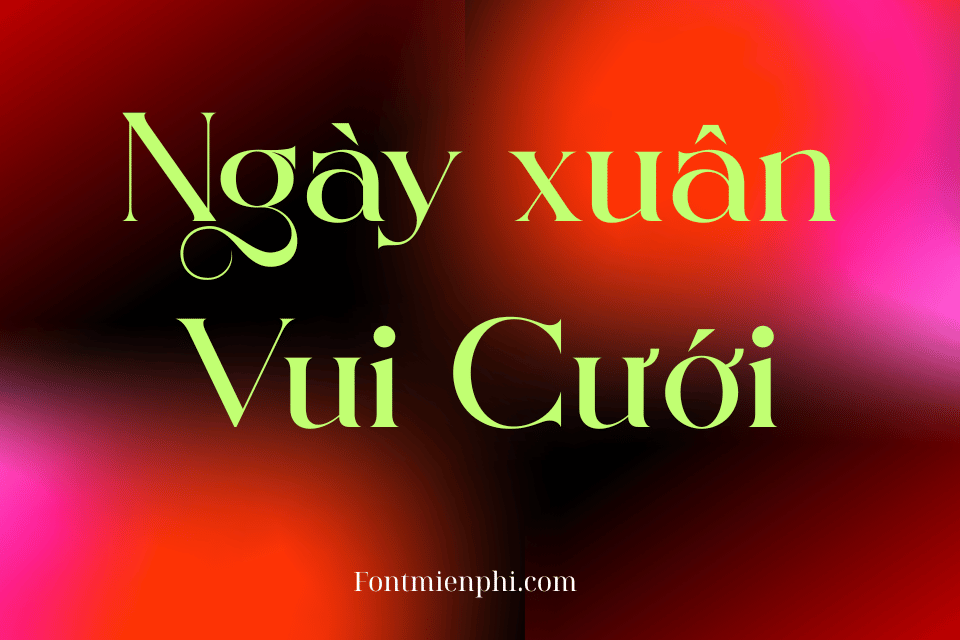
Font Việt Hóa 1FTV VIP Gerlomi – “Đắt Nét Xuân” Cho Thiết Kế Tết
- Kiểu chữ bay bổng, thanh lịch: Nét mảnh kết hợp hoa văn Tết truyền thống (cành đào, lá mai, họa tiết lụa).
- Tối ưu cho tiếng Việt: Full bộ dấu, hỗ trợ đa dạng font weight (từ Light đến Bold).
- Chất VIP: Phủ vàng/đỏ trong bản Pro, dễ dàng blend màu với background Tết.
Ứng dụng “hot” Tết 2025:
- Thiệp chúc mừng, banner “Lộc Xuân Thịnh Vượng”.
- Poster quảng cáo Tết (rượu bia, bánh mứt, hàng cao cấp).
- Profile công ty phiên bản Tết (dành cho đối tác).
Gợi ý kết hợp:
“Gerlomi không chỉ là font – là tinh hoa Tết trong từng nét chữ!”